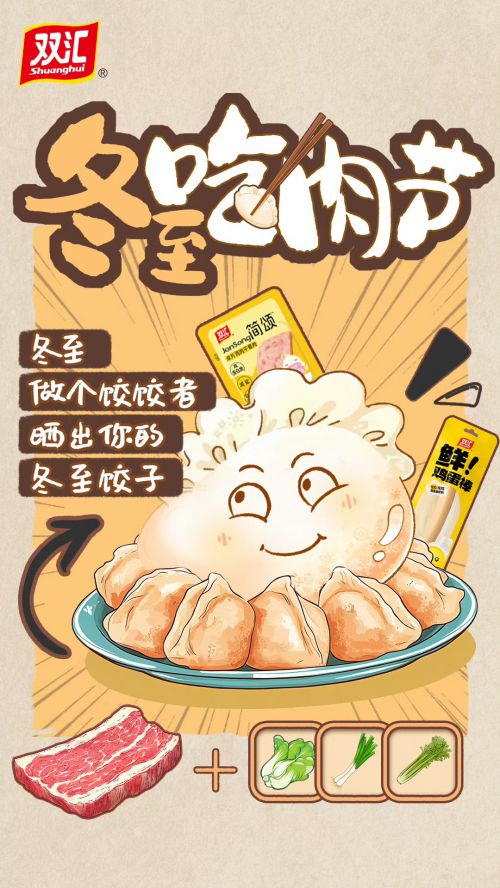
龚帆免费体
### 龚帆免费体:硬朗风格手写体,免费商用首选 龚帆免费体是由龚帆字库推出的免费商用手写体,以硬朗的手写风格和实用的字形设计为核心特点。作为粗字重手写体,字体整体字形方正,重心居中且中宫适中,确保视觉平衡与阅读舒适度。 该字体采用独特的直角笔型设计,搭配方头笔画与断开式结构,形成兼具力量感与手写温度的视觉效果。字重饱满均匀,笔画线条粗而有力,既保留手写字体的随性特质,又通过均匀的粗细控制增强设计稳定性,适合各类标题与正文排版。 作为免费商用字体,龚帆免费体支持简体中文常规字符集,适用于海报标题、包装设计、社交媒体配图等多种场景,为创作者提供兼具个性与实用性的文字选择。